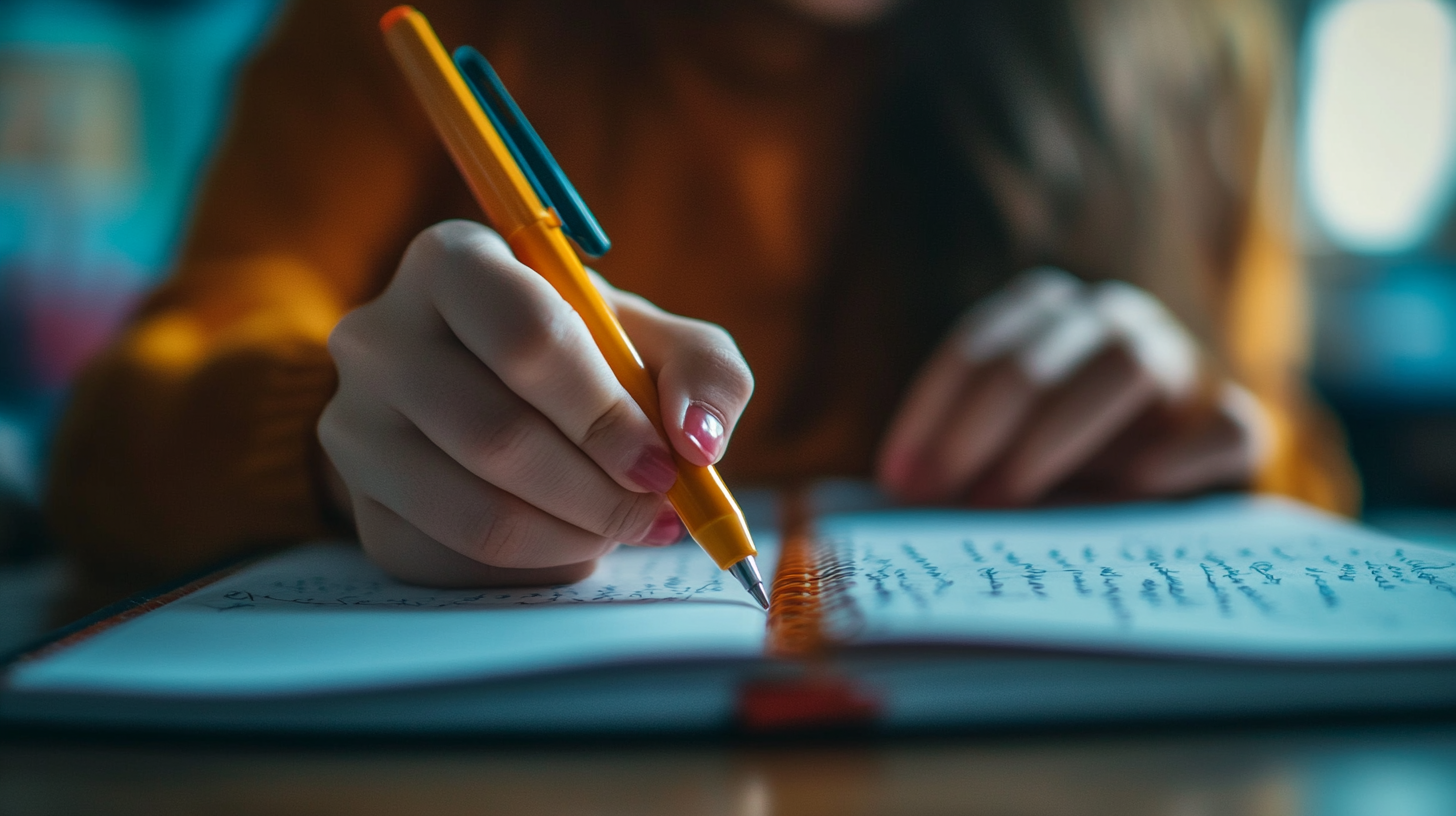
"좋은 연습장을 사용하면 글씨가 더 좋아질까?" 🤔 물론 도움이 되지만, 글씨 교정의 핵심은 연습장보다 더 중요한 요소들이 있어요! ✍ 예쁜 글씨체를 만들려면 손의 움직임, 필기구 선택, 필기 습관이 더 중요한 역할을 한답니다.
오늘은 연습장보다 더 중요한 글씨 교정의 핵심 요소들을 알아볼게요! 🚀
📄 연습장만으로 글씨 교정이 어려운 이유
많은 사람들이 글씨 교정을 위해 비싼 연습장을 구매하지만, 실제로는 연습장만으로는 글씨가 쉽게 교정되지 않아요. 🤔 좋은 연습장이 도움이 될 수는 있지만, 필기 습관, 손의 움직임, 필기구 선택이 훨씬 더 중요하답니다! ✍
그렇다면 연습장만으로 글씨 교정이 어려운 이유는 무엇일까요?
✅ 필기 자세와 손의 움직임이 잘못되면 아무리 써도 효과가 없음
✅ 필기구가 본인에게 맞지 않으면 획이 흔들릴 수 있음
✅ 자간과 행간을 맞추는 연습이 부족하면 정돈된 글씨체가 나오지 않음
📌 연습장만으로 해결되지 않는 문제들
문제점 설명 🪑 잘못된 필기 자세 허리를 구부리거나 손목에 힘이 과도하게 들어감 🖊 필기구 선택 문제 손에 맞지 않는 펜을 사용하면 획이 일정하지 않음 📏 자간 & 행간 불균형 글자 간격이 일정하지 않아 정돈된 글씨가 나오지 않음 연습장만 바꿔도 글씨가 좋아질 거라고 생각했다면, 이제 진짜 중요한 요소들을 체크해봐야겠죠? 😊 다음으로 글씨 교정의 핵심 요소 3가지를 알아볼까요? ✨
🎯 글씨 교정의 핵심 요소 3가지
연습장보다 더 중요한 것은 글씨를 교정하는 핵심 요소를 정확히 알고 올바르게 연습하는 것이에요! ✍ 아무리 좋은 노트를 써도 잘못된 방법으로 연습하면 효과가 없어요. 🤔
글씨 교정의 핵심 요소 3가지는 ✅ 바른 필기 자세 유지하기 ✅ 손에 맞는 필기구 선택하기 ✅ 자간과 행간을 일정하게 맞추는 연습하기 이 세 가지예요! 🚀
📌 예쁜 글씨체를 만들기 위한 필수 요소
핵심 요소 설명 🪑 바른 필기 자세 허리와 손목을 올바르게 유지해야 글씨가 안정적 🖊 필기구 선택 손에 맞는 연필이나 펜을 사용하면 획이 일정해짐 📏 자간 & 행간 조절 글자 간격을 일정하게 유지해야 깔끔한 글씨체 완성 이제 바른 필기 자세와 손의 움직임을 구체적으로 알아볼까요? 😊
🪑 바른 필기 자세와 손의 움직임
아무리 좋은 연습장을 사용해도 필기 자세가 잘못되면 글씨가 흐트러질 수 있어요. 🤔 특히 허리를 구부리거나 손목에 힘이 과하게 들어가면 획이 일정하지 않고, 필기할 때 손이 쉽게 피로해져요. ✍
따라서 글씨 교정의 첫걸음은 바른 필기 자세 유지하기! ✅ 허리를 곧게 펴고, 팔꿈치를 책상에 살짝 올리기 ✅ 손목에 힘을 빼고, 부드럽게 움직이기 ✅ 필기구를 너무 세게 쥐지 않기 이 세 가지만 지켜도 글씨체가 훨씬 안정적이 될 수 있어요! 🚀
📌 글씨체를 개선하는 바른 필기 습관
필기 자세 설명 🪑 허리 곧게 펴기 등을 구부리지 않고 바른 자세 유지 ✋ 손목 힘 빼기 손목에 긴장이 들어가지 않도록 부드럽게 움직이기 🖊 필기구 가볍게 쥐기 필기구를 너무 꽉 쥐지 않고 편안하게 잡기 바른 자세를 유지하면 손이 덜 피곤하고, 글씨체가 더욱 깔끔해져요! 😊 그렇다면 필기구 선택이 글씨체에 어떤 영향을 미칠까요? 🤔
🖊 필기구 선택이 글씨체에 미치는 영향
"좋은 필기구를 사용하면 글씨가 더 좋아질까?" 🤔 정답은 YES! 필기구의 종류에 따라 획의 흐름, 글씨의 균형, 필기 속도가 달라질 수 있어요. ✍ 특히 자신에게 맞는 필기구를 선택하면 글씨체가 훨씬 더 안정적이고 정돈된 느낌을 줄 수 있답니다! 😊
필기구 선택이 중요한 이유
✅ 연필, 볼펜, 만년필마다 필기감이 다름
✅ 손에 맞는 두께와 무게의 필기구를 선택해야 피로도가 줄어듦
✅ 필기구에 따라 획의 굵기와 균형이 달라질 수 있음 🚀
📌 필기구 종류별 특징 & 추천
필기구 특징 추천 용도 ✏ 연필 (2B~4B) 필압 조절이 쉬워 초보자에게 적합 획 연습, 기본 필기체 교정 🖊 유성 볼펜 (0.5mm) 획이 선명하고 빠른 필기 가능 실전 필기, 빠른 노트 정리 🖋 만년필 (EF/F촉) 획의 굵기 변화가 가능하여 세련된 필체 완성 필사 연습, 정돈된 필기체 훈련 자신에게 맞는 필기구를 선택하면 획이 더욱 일정하고 부드러워질 수 있어요! 😊 이제 자간과 행간 조절 연습이 왜 중요한지 알아볼까요? 🤔
📏 자간과 행간 조절 연습이 필수인 이유
글씨를 아무리 또박또박 써도 자간(글자 사이 간격)과 행간(줄 간격)이 불규칙하면 지저분해 보일 수 있어요. 😵 그래서 자간과 행간을 맞추는 연습은 예쁜 글씨체를 만들기 위한 필수 과정이에요! ✍
자간과 행간을 일정하게 맞추면
✅ 글씨가 정돈되어 보이고
✅ 가독성이 좋아지며
✅ 필기 속도를 조절하기 쉬워져요! 🚀
📌 자간 & 행간을 일정하게 맞추는 연습법
연습 방법 설명 📏 일정한 자간 유지 글자 간격을 일정하게 맞춰 균형 있는 필체 만들기 📖 모눈 노트 활용 모눈 종이를 이용해 글자 크기와 간격을 맞추는 연습 📐 수직 정렬 훈련 줄 맞춤을 정확히 해서 정리된 글씨 쓰기 자간과 행간을 맞추는 연습을 꾸준히 하면 더 정돈된 필체를 만들 수 있어요! 😊 이제 꾸준한 연습을 위한 루틴 만들기를 알아볼까요? ✨
⏳ 꾸준한 연습을 위한 루틴 만들기
글씨 교정은 단기간에 끝나는 것이 아니라 꾸준한 연습이 필수예요! ✍ 하루 10~15분 정도만 투자해도 한 달 후에는 눈에 띄는 변화를 볼 수 있어요! 😊
꾸준한 연습을 위한 루틴
✅ 획 연습 → 글자 연습 → 문장 필사 순서로 진행하기
✅ 하루 10~15분씩 짧게라도 꾸준히 연습하기
✅ 필기 전 손 스트레칭을 해서 손의 긴장 풀기 이렇게 하면 부담 없이 글씨 교정을 할 수 있어요! 🚀
📌 하루 10분 루틴 - 글씨 교정 플랜
시간 연습 내용 효과 3분 기본 획 연습 (직선, 곡선, 점 연결) 획의 균형과 힘 조절 능력 향상 4분 한글 글자 연습 (자간 & 행간 맞추기) 글씨 정렬 및 가독성 향상 3분 좋아하는 문장 필사 필기 속도 조절 및 글씨체 안정화 꾸준한 연습 루틴을 정하면 글씨 교정이 더 쉬워지고 빠른 변화를 볼 수 있어요! ✍ 이제 글씨 교정에 대한 자주 묻는 질문(FAQ)을 살펴볼까요? 🤔
Q1. 연습장 종류에 따라 글씨 교정 효과가 달라질까요?
A1. 어느 정도 영향이 있어요! ✍ 모눈 노트나 가이드라인이 있는 노트를 사용하면 자간과 행간을 일정하게 맞추기 쉬워요. 하지만 노트보다 더 중요한 것은 올바른 필기 습관과 연습 루틴이에요! 😊
Q2. 하루 몇 분씩 연습해야 글씨 교정이 가능할까요?
A2. 하루 10~15분 정도 꾸준히 연습하면 2~4주 안에 눈에 띄는 변화를 볼 수 있어요! 🚀 핵심은 짧게라도 매일 연습하는 것이에요. 😊
Q3. 필기구에 따라 글씨체가 달라질까요?
A3. 네! 연필, 볼펜, 만년필 등 필기구마다 필기감이 달라요. 초보자는 2B 연필로 연습하는 것이 좋고, 실전 필기에서는 유성 볼펜(0.5mm 이하)이 적합해요! 🖊
Q4. 필사 연습을 하면 글씨가 더 좋아질까요?
A4. 네! 📖 필사는 글씨의 균형과 흐름을 익히는 데 매우 효과적이에요. 책 속 문장, 명언, 노래 가사 등을 따라 써보면 획과 자간을 자연스럽게 조절하는 능력이 길러져요! 😊
Q5. 필기 속도를 높이면서도 글씨를 예쁘게 쓰는 방법이 있나요?
A5. 처음에는 천천히 쓰면서 균형을 맞추는 것이 중요해요. ⏳ 그 후 점점 속도를 높이면서도 획의 흐름과 자간을 유지하는 연습을 하면 빠르게 써도 깔끔한 글씨체를 만들 수 있어요! 🚀
Q6. 글씨를 쓸 때 손목이 아픈 이유는 무엇인가요?
A6. 손목에 과도한 힘이 들어가거나 잘못된 필기 자세 때문일 가능성이 커요! 💪 필기 전 손 스트레칭을 해주고, 필기구를 너무 꽉 쥐지 않도록 신경 써보세요. 😊
Q7. 필기 자세가 글씨체에 영향을 주나요?
A7. 네! 🪑 허리를 구부리거나 손목에 힘이 많이 들어가면 글씨체가 쉽게 흐트러질 수 있어요. 허리를 곧게 펴고, 손목에 힘을 빼고 필기하는 습관을 들이면 더 깔끔한 글씨체를 만들 수 있어요! ✍
Q8. 꾸준한 연습을 위해 어떻게 동기부여를 하면 좋을까요?
A8. 연습 과정을 기록하는 것이 좋아요! 📸 글씨를 연습하기 전과 후의 변화를 사진으로 남기거나, SNS에 공유하면서 작은 목표를 세우면 더 꾸준히 연습할 수 있어요. 😊
이제 글씨 교정을 위한 모든 핵심 요소를 배웠어요! 🎉 연습장보다 더 중요한 것들을 기억하고 꾸준히 연습해서 예쁜 글씨체를 만들어보세요! ✍✨